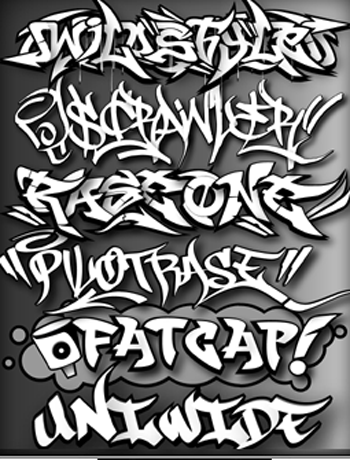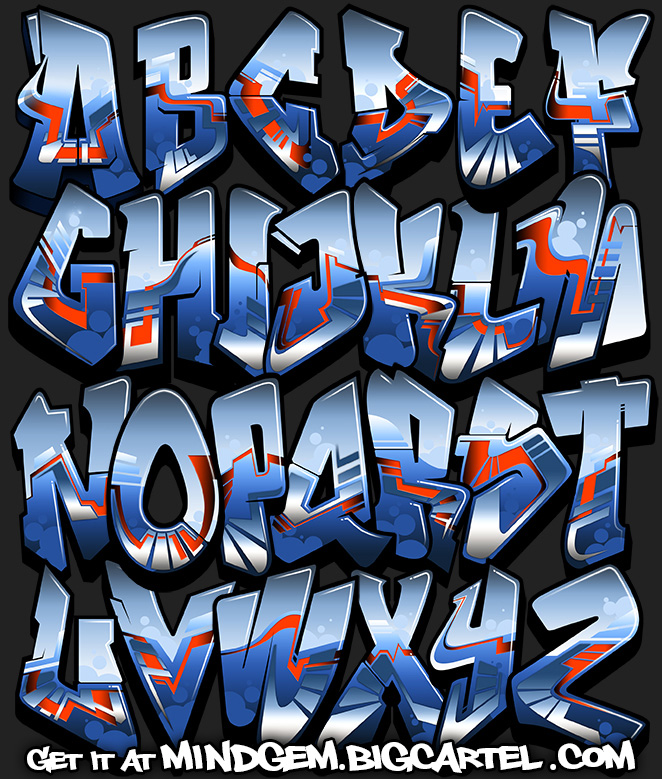
Выбор шрифта — это ответственный процесс, так как формы букв могут усилить или наоборот исказить нужный смысл сообщения. У каждого шрифта есть свой характер. Этот характер может быть ярким или приближенным к нейтральности. Но так же как не бывает живого человека без эмоций, не бывает и абсолютно нейтрального шрифта. Поэтому, попробуем разобраться, какие существуют признаки форм букв, усиливающие и ослабляющие яркость шрифта.
Самый главный признак шрифта, влияющий на яркость его характера — это его непривычность, необычность, новизна. Есть крылатая фраза знаменитой Сюзанны Личко: «We read best what we read most». Мы читаем лучше всего то, что читаем чаще всего. Чем чаще мы видим буквы, тем сильнее их формы закрепляются в сознании читателей и увеличивается скорость распознавания знаков. Буквы становятся привычными. Но если этот процесс привыкания из-за частоты использования делает любой шрифт более нейтральным, значит (к сожалению) со временем угасает яркость характера любого шрифта.
Поэтому, при выборе шрифта нужно выяснить, как часто он используется. Если шрифт заезженный, измученный частыми неуместными использованиями, его акцидентные качества, его инструменты выразительности ослаблены. Такой шрифт нужно отложить в сторону, чтобы его яркость восстановилась, укрепилась. Если существует какая-то группа шрифтов, часто используемых для длинных текстов, то даже недавно созданный новый шрифт, относящийся к этой группе, будет казаться менее выразительным. И наоборот: хорошо забытый старый шрифт и совершенно новый шрифт с формами, отличающимися от современных стереотипов нейтральности, будут вызывать у читателей шок, удовольствие удивления и восторга.
Второй признак, важный при выборе характера шрифта, — это временная эпоха. У шрифтов есть история эволюции форм. Каждая уникальная форма буквы появилась в определённый промежуток времени, поэтому каждая форма соответствует какому-либо этапу развития человеческой культуры. Поэтому, при выборе возникает вопрос уместности форм букв шрифта, исторического соответствия форм букв и смысла сообщения. Если, например, мы подбираем шрифт для сообщения современности, актуальности, то нельзя ошибиться и использовать шрифт с отсылкой к древним архаичным формам. Если мы умышленно смешиваем эпохи, то эта смесь должна быть чёткой. Читателю должно быть понятно, зачем это сделано. Чтобы не ошибиться, можно воспользоваться вот таким списком соответствия основных форм букв временным периодам. Для русских букв это этапы:
3 век—9 век — Черты и резы. Линии на бересте, дереве, глине, камнях.
863 г. — Глаголица. Азбука для записи религиозных текстов.
893 г. — Кириллица. Устав.
13 век — Вязь.
Начало 14 века — Полуустав.
Вторая половина 14 века — Скоропись.
Конец 15 века — В Европе появляются гуманистические антиквы.
Первая половина 16 века — Появляется итальянский курсив (italic).
Вторая половина 16 века — Первые печатные шрифты на основе полуустава.
1708—1710 гг. Реформа Петра 1. Возникновение гражданского шрифта на основе европейских антикв 17 века.
Середина 18 века — Переходные антиквы. Развитие почерков остроконечным пером.
1816 — William Caslon IV создаёт первый гротеск — шрифт без засечек для заголовков.
Конец 18—начало 19 века — Классицистические контрастные антиквы.
Вторая половина 19 века — Декорированные антиквы. Брусковые. Акцентированный обратный контраст.
1890 — Распространяются старые гротески со строчными буквами Akzidenz Grotesk.
Начало 20 века — Появляются контрастные гротески (антиквы без засечек).
1920-е — Появление геометрических гротесков Futura и Erbar.
1910—30-е — Появление узких геометрических гротесков DIN.
1950—1960 — Появление неогротесков Helvetica, Univers. Появление ленточных антикв Optima. Первые кириллизации неогротесков.
1970-е — Появление модульных шрифтов для устройств с низким разрешением: принтеров, компьютеров.
1980-е — Оцифровка шрифтов.
1990-е — Появление экспериментальных эклектичных шрифтов. Развитие стиля гранж в типографике.
Активное искажение форм.
2000-е — Создание цифровых шрифтов на основе всех видов письма. Появление вариативных шрифтов. Появление шрифтов, предназначенных специально для интерфейсов и экранов.
Это короткий список, чтобы быстро ориентироваться, к какому периоду можно шрифт отнести. В проектах, где важна историческая достоверность, нужно проводить исследования, искать источники, образцы для сверки.
Третьим признаком характера шрифта является противопоставление человечность-искусственность. Есть разные способы образования форм букв. Какие-то буквы рисует человеческая рука. Другие буквы созданы машинами или с помощью искусственных инструментов. Какие-то формы букв отсылают к человеческим почеркам и рисункам. Другие формы основаны на абстрактных геометрических примитивах (окружность, треугольник, квадрат и т.д.). Поэтому, выделяют два принципа построения шрифтов: гуманистический (human=человек) и геометрический. Иногда эти принципы смешиваются.
Гуманистические шрифты в качестве основы форм имеют три основных принципа построения штриха буквы:
- Постоянный по толщине штрих.
Например, нарисованный шариковой ручкой. - Штрих с расширением. Например, написанный остроконечным пером или брашпеном.
- Штрих с переносом ширины. Например, написанный ширококонечным пером или широкой палочкой.
Чем отличаются эти принципы и как они влияют на формы букв в современных шрифтах можно прочитать в небольшой книжке Геррита Ноордзея «Штрих. Теория письма».
Кроме распределения ширин штрихов, буквы отличаются и формой скелетов букв (скелет буквы — аллограф). Например, штрихи могут быть более выгнутыми или более прямыми. Завершаться каплей или засечкой. Могут стыковаться в разных местах. Скелеты букв тоже могут быть заимствованы из живых почерков, либо быть искусственно выдуманными абстрактными формами.
Примерьте на размер
Если вы не уверены, подходят ли эти шрифты для вас или вашего проекта, зайдите в наш раздел бесплатных шрифтов, где мастера и графические дизайнеры найдут отличные бесплатные шрифты для граффити! Кто не любит пробовать перед покупкой! Конечно, если вы большой поклонник этого шрифта в уличном стиле, тогда вы готовы просмотреть все лучшие шрифты для граффити, которые мы можем предложить, и есть из чего выбрать! Возьмите один из этих потрясающих шрифтов в стиле граффити сегодня и повеселитесь!